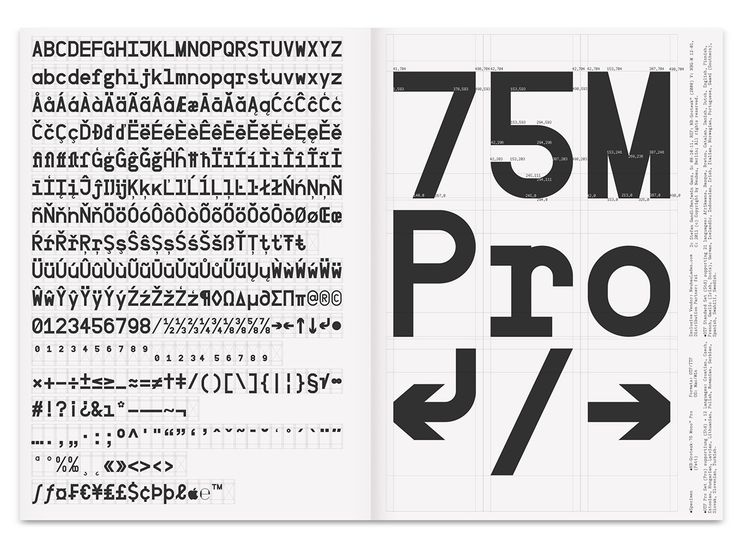
Как правильно выбрать шрифт для книги?
текст: Валерий ЛеденёвВ Москве на фестивале книжного дизайна «Жар-книга» с лекциями выступили два известных швейцарских специалиста — Франсуа Раппо и Йонас Фёгели.
Валерий Леденёв расспросил Фёгели о принципах его работы.
— Не могу не задать самого общего и наивного вопроса — зачем книге нужен дизайн?
— Конечно, книга — это, в первую очередь, носитель информации и хранитель знания. Но в культуре всегда важна коммуникация. И графический дизайн в определенном смысле осуществляет функцию перевода. С читателем необходимо коммуницировать. Если дизайн хороший, он облегчает доступ к культуре. Если он сделан плохо и небрежно, культурный материал рискует быть утраченным.
— Получается, что, издавая книгу в переводе на другой язык, дизайн книги также нужно определенным образом «переводить»?
— Существуют вещи, которые можно передать «один к одному». Например, для книги, изданной на немецком языке, существуют правила набора текста или форматирования, которые можно «перевести», работая с кириллицей. В некоторых своих книгах я часто обращаюсь к метафорам в концептуальной структуре издания, разным возможностям построения в нем нарратива.
В одной моей работе, например, один рассказ воспроизводится трижды, но с различных точек зрения. Такие вещи будет легко адаптировать при «переводе». Однако кое-что (например, ту же типографику), вполне вероятно, придется переделать полностью.
— Может ли профессиональный дизайнер иметь свои предпочтения в смысле материала, с которым работает, или же он должен уметь спроектировать издание на любую тему?
— Мое собственное мнение всегда играет существенную роль. Есть клиенты, с которыми я ни за что не стал бы сотрудничать, с другими по завершении работы мы становились хорошими друзьями. То же касается изображений. Работа по их отбору всегда внушительна и масштабна. Например, во время работы над одной книгой на нас свалилось около десяти тысяч произведений одного художника, но в издании мы смогли опубликовать лишь шестьсот. В этом случае, конечно же, мы глубоко были вовлечены в процесс отбора.
Вы увидите свой текст немного по-другому и, возможно, сможете заметить ошибки или взглянуть на свою работу свежим взглядом.
Это может помочь автору самостоятельной публикации получить лучший результат с помощью своего редактора. И это может помочь традиционно публикуемому автору, предлагающему книгу издателю или агенту, сменить шрифт.
Книга становится высказыванием. И это важно, потому что она посвящена сквотам, уличным протестам, демонстрациям.